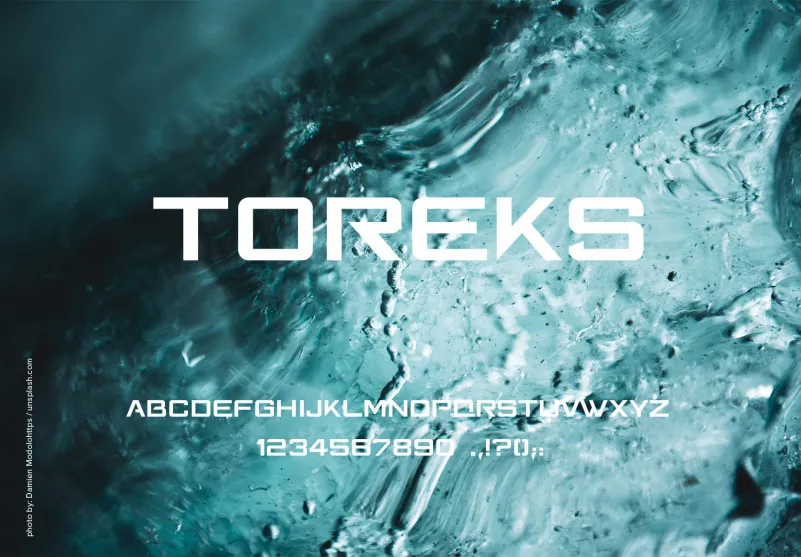
A Toreks Font é uma elegante escolha para aqueles que buscam uma fonte sans serif moderna e futurista. Desenvolvida pela asysr86, ela tem um toque de estilo esportivo que parece claramente inspirado em corridas de carros. Esta fonte está perfeitamente adaptada para aplicações digitais, tanto nas redes sociais quanto nos websites modernos. Seus traços finos e linhas elegantes também oferecem uma aparência atraente para designs impressos, como posters ou materiais de marketing. A Toreks é ideal para o design do conteúdo em tempo real, ajudando você a criar um visual inovador e único que chamará atenção. Seja para uso em postagens na mídia social, logos ou até mesmo camisetas com mensagens impactantes, ela se ajusta perfeitamente. Todas essas possibilidades são apenas o começo da criatividade: a Toreks é uma fonte versátil e moderna que não apenas combina bem em ambientes digitais, mas também transmite uma energia futurista capaz de cativar qualquer público. Seja você um designer gráfico ou um designer de moda, a Toreks será definitivamente uma opção valiosa para estabelecer seu próprio estilo único no design digital.